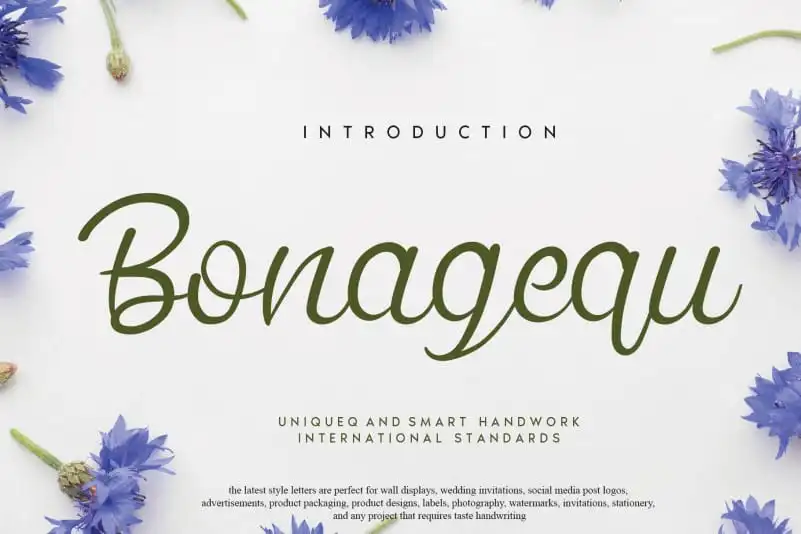
Bonagequ Script Font – Download Grátis
A Bonagequ Script Font é uma criação criativa dos talentosos designers do andikastudio que oferece uma experiência única para seus projetos digitais e impressos. Com seu traço fluido e elegante, a Bonagequ Script traz um toque de sofisticação e originalidade às suas mensagens escritas à mão. Esta fonte handwritten combina facilmente elementos de estilo vintage com nuances modernas, o que cria uma experiência visual envolvente e natural. Para quem procura uma fonte única que transmite confiança e personalização, a Bonagequ Script é perfeita para enriquecer seus projetos. Seja no design gráfico, na publicidade ou nas artes digitais, essa fonte oferece o que há de melhor em elegância handwritten.